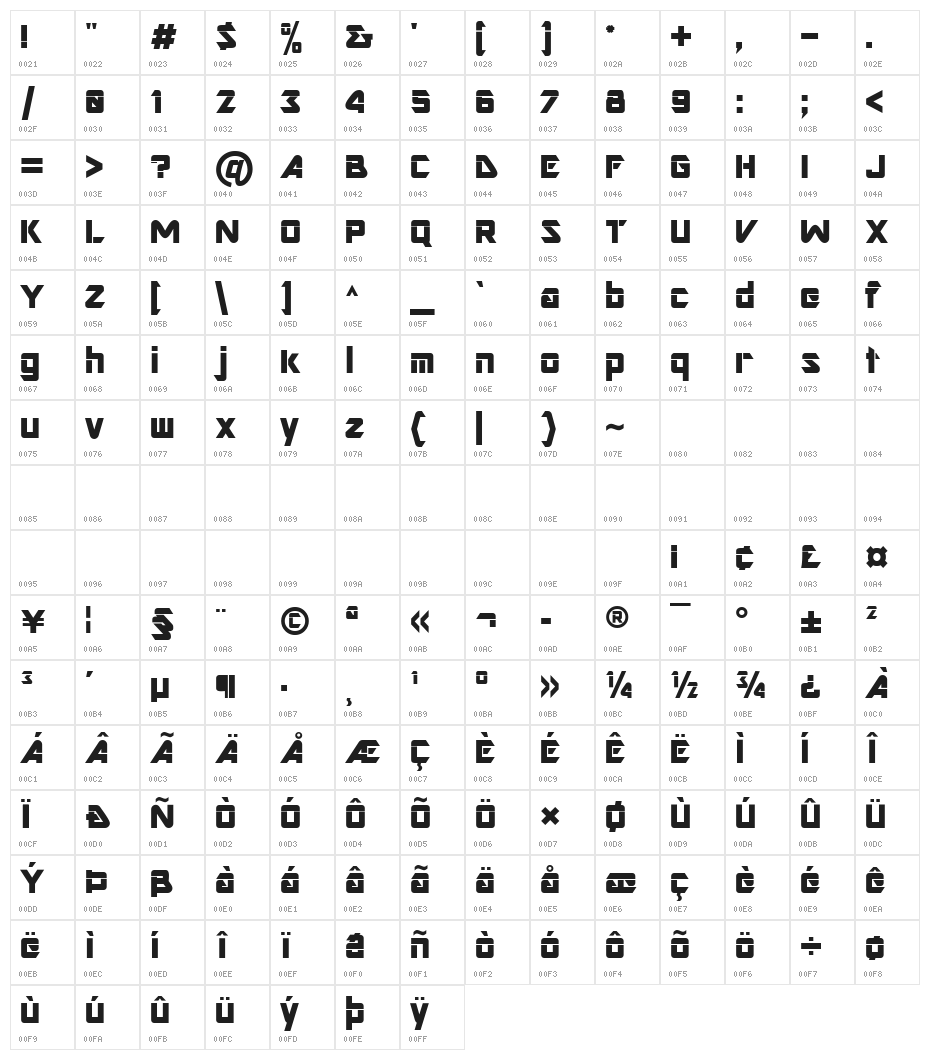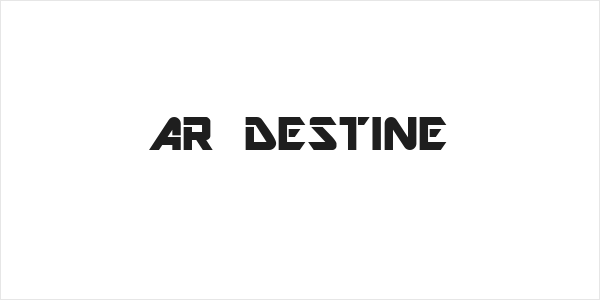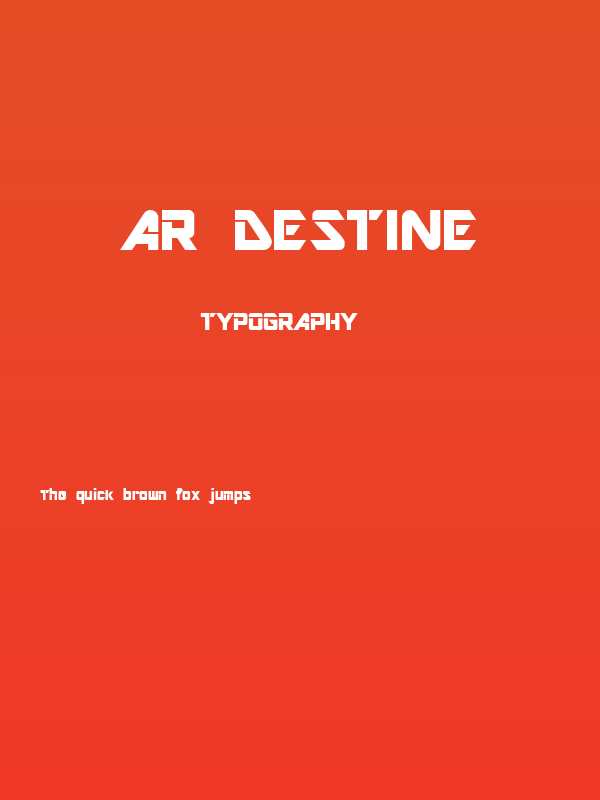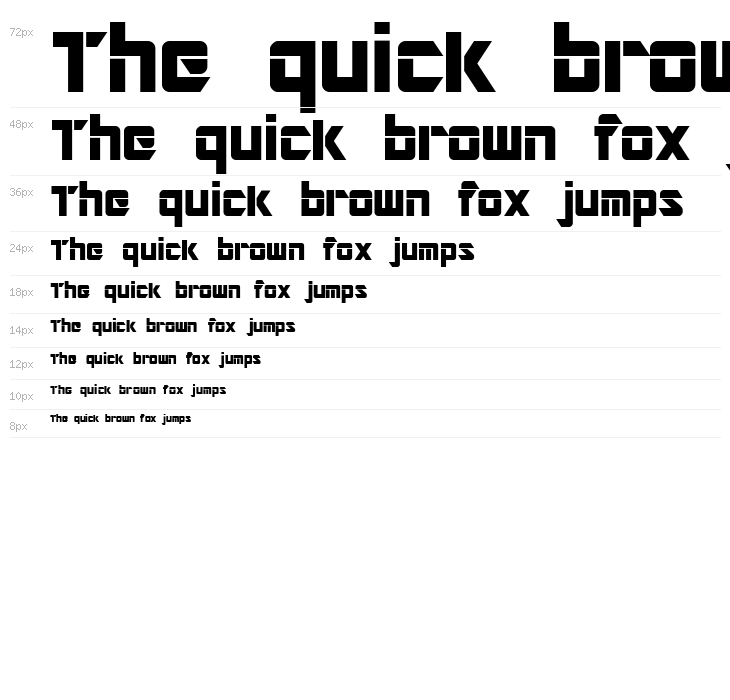
AR DESTINE Font
AR-DESTINE 大文字
AR-DESTINE 小文字
AR-DESTINE その他の文字
| おすすめプロジェクト | Ideal for sci-fi themed posters, video game titles, branding for tech companies, and any project needing a modern, impactful look. |